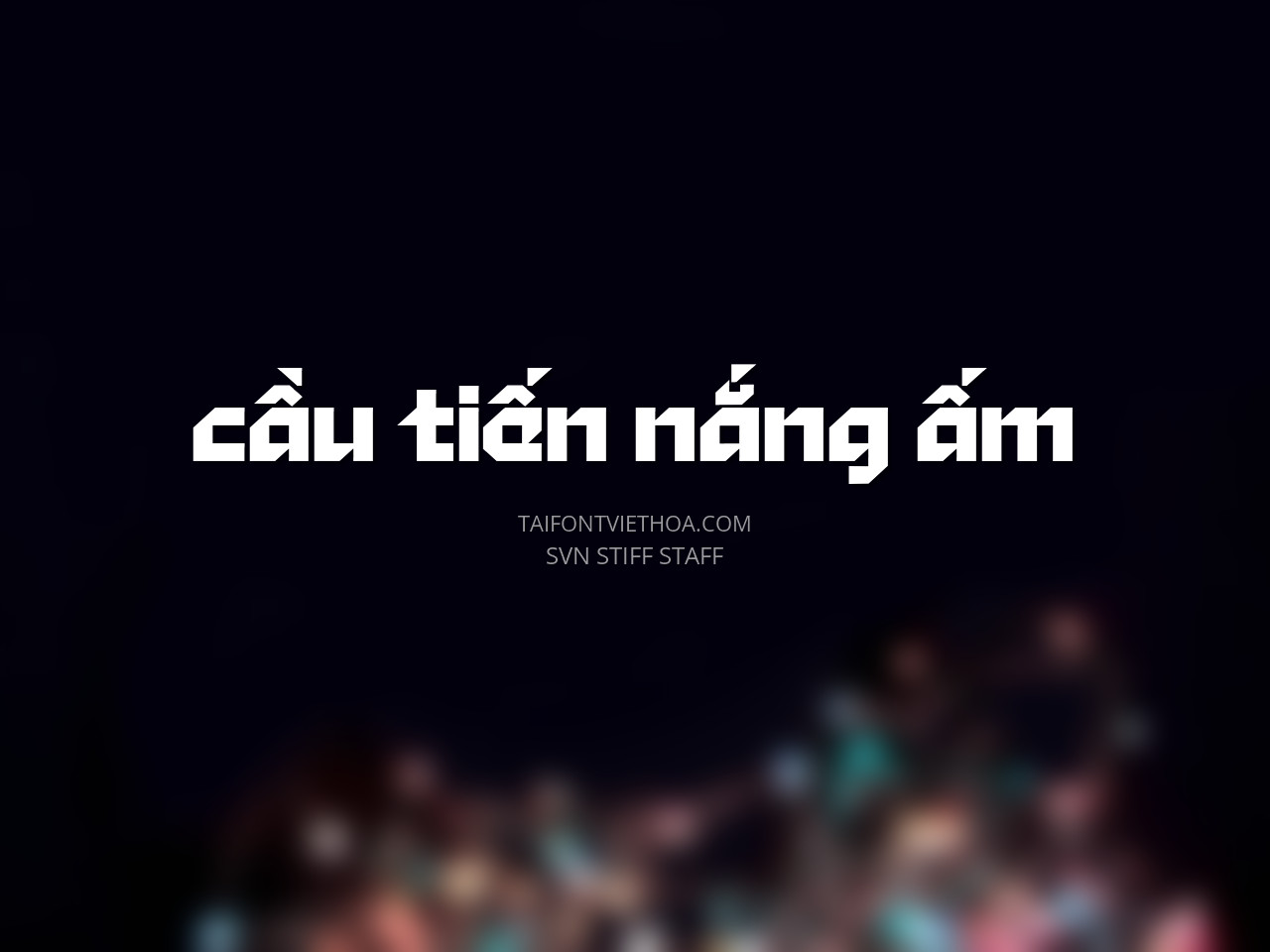
Font việt hóa SVN Stiff Staff
Tác giả Font: Borislav Alexandrov
Giới thiệu về Stiff Staff – Font display retro, cá tính mạnh mẽ
Stiff Staff (tên gốc: Stiff Staff Typeface) là phông chữ display độc đáo được thiết kế bởi Dani (Letterhend Studio)và phát hành trên Creative Market từ năm 2019. Lấy cảm hứng từ bảng hiệu cổ điển và typography quảng cáo Mỹ đầu thế kỷ 20, Stiff Staff sở hữu các đường nét vuông vức, góc cạnh, kết hợp cùng chi tiết bo tròn nhẹ giúp font vừa cứng cáp, vừa thân thiện. Bản quốc tế của Stiff Staff hỗ trợ trên 60 ngôn ngữ Latin, tích hợp bộ ký tự đặc biệt, ligature và số đầy đủ, cho phép ứng dụng linh hoạt trên cả thiết kế số và in ấn chuyên nghiệp.
Phiên bản SVN Stiff Staffđã được STYLEno.1 FontsViệt hóa trọn bộ: bổ sung dấu tiếng Việt, cân chỉnh lại kerning và tối ưu hóa hinting giúp font hiển thị sắc nét ở mọi kích thước. Đội ngũ taifontviethoa.comđã kiểm thử thực tế trên nhiều phần mềm thiết kế như Photoshop, Illustrator, Canva… đảm bảo font luôn mượt mà, không lỗi dấu, không vỡ nét. Nhờ đó, Stiff Staff Việt hóa sẵn sàng đáp ứng mọi nhu cầu sáng tạo về branding, poster, bao bì hoặc các dự án thiết kế cần nét cổ điển pha lẫn cá tính đương đại.
Đặc điểm thiết kế, ứng dụng và ngành nghề phù hợp
Stiff Staff thuộc nhóm display vintage (cổ điển)với cấu trúc chữ dày dặn, các góc cạnh khỏe khoắn và đầu nét bo tròn nhẹ tạo điểm nhấn đặc trưng. Font này đặc biệt phù hợp làm tiêu đề lớn, logo, bảng hiệu, poster sự kiện hoặc nhãn sản phẩm handmade. Các ligatures và alternates phong phú giúp cá nhân hóa từng thiết kế, mang lại hiệu ứng thị giác đậm chất retro nhưng vẫn giữ sự mới mẻ, trẻ trung cho tổng thể bố cục.
Ứng dụng tiêu biểu
– Logo & nhận diện:Studio nghệ thuật, shop thời trang vintage, thương hiệu thủ công, quán café.
– Ấn phẩm quảng cáo:Poster sự kiện, banner quảng cáo, biển hiệu, story social media.
– Bao bì & nhãn mác:Sản phẩm thủ công, hộp quà, nhãn mác mỹ phẩm, sổ tay sáng tạo.
Ngành nghề phù hợp